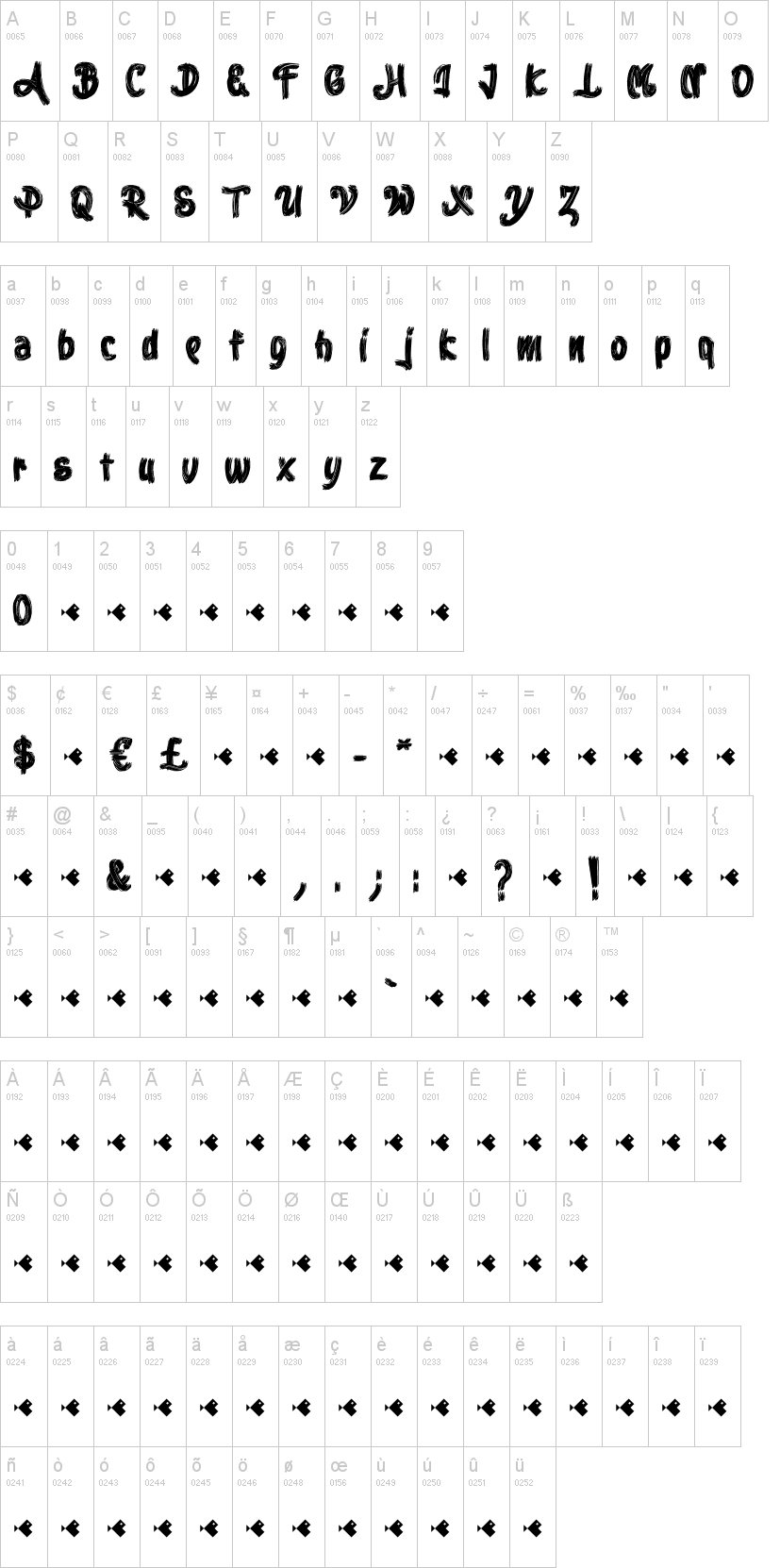
Stoica Brush
Stoica Brush 字体是一种手写风格的字体,其设计灵感来自于创作者的个人笔迹。这款字体的设计者是来自罗马尼亚的设计师Andrei Ștefan Stoica,因此该字体的名称也以他的名字命名。 Stoica Brush 字体的特点在于它的笔画流畅自然,仿佛是手写的效果。该字体的笔画粗细不一,弯曲的部分更加突出,从而增强了字体的艺术感。该字体支持多种语言的字符,包括西欧语言和中东语言。 Stoica Brush 字体的应用非常广泛,可以用于海报、标志、广告、名片等多种设计场合。由于该字体的字母形状独特,因此也受到许多平面设计师和艺术家的喜爱。
Stoica Brush是一款非常不错的手写艺术字体,具有很好的视觉感,适合于文化类的宣传设计、商业类品牌的广告和产品包装设计以及个性化文字排版等较多场景。
Stoica Brush字符映射图